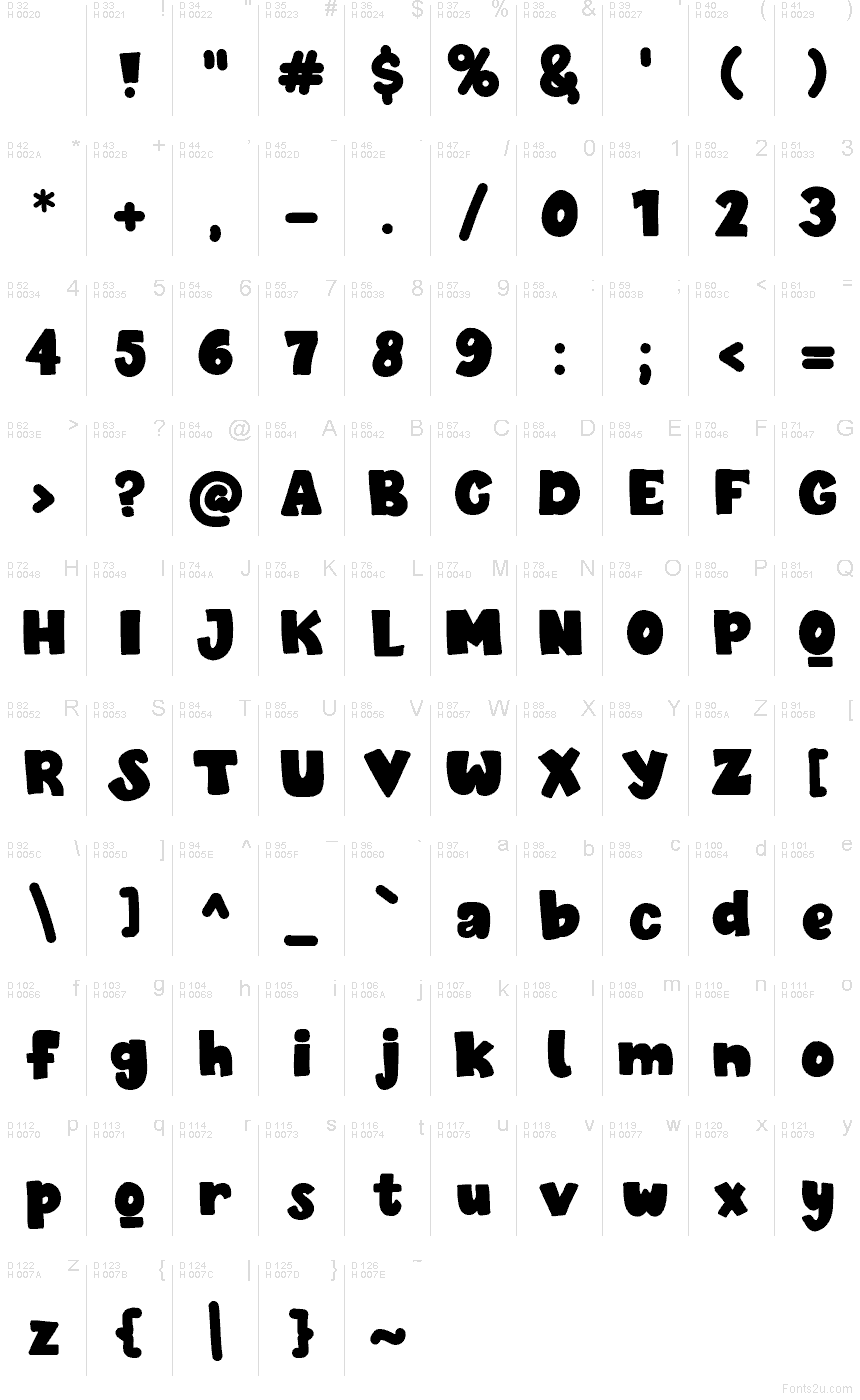
Slumber Dog من Letterstock Std هو خط عرض كرتوني مجاني، يتميز بأشكال ناعمة وذات طابع يحاكي النعاس. تمنح الحروف المستديرة والمنتفخة مع خط علوي غير منتظم قليلاً إيقاعاً ناعماً يشبه أشكال الألعاب القطنية المحشوة أكثر من كونه خطاً عادياً للقصص المصورة.
هذه الحيوية اللطيفة تجعله خياراً مثالياً لأغلفة كتب الأطفال، ودعوات حفلات البيجاما، وتصاميم ديكورات غرف الأطفال، وعبوات الوجبات الخفيفة، وصور الفيديوهات المصغرة على يوتيوب. يبرز الخط بشكل أفضل في العناوين القصيرة، حيث تخلق منحنياته الشبيهة بالوسائد نبرة ودودة ومريحة، بدلاً من إعطاء انطباع بالمبالغة.